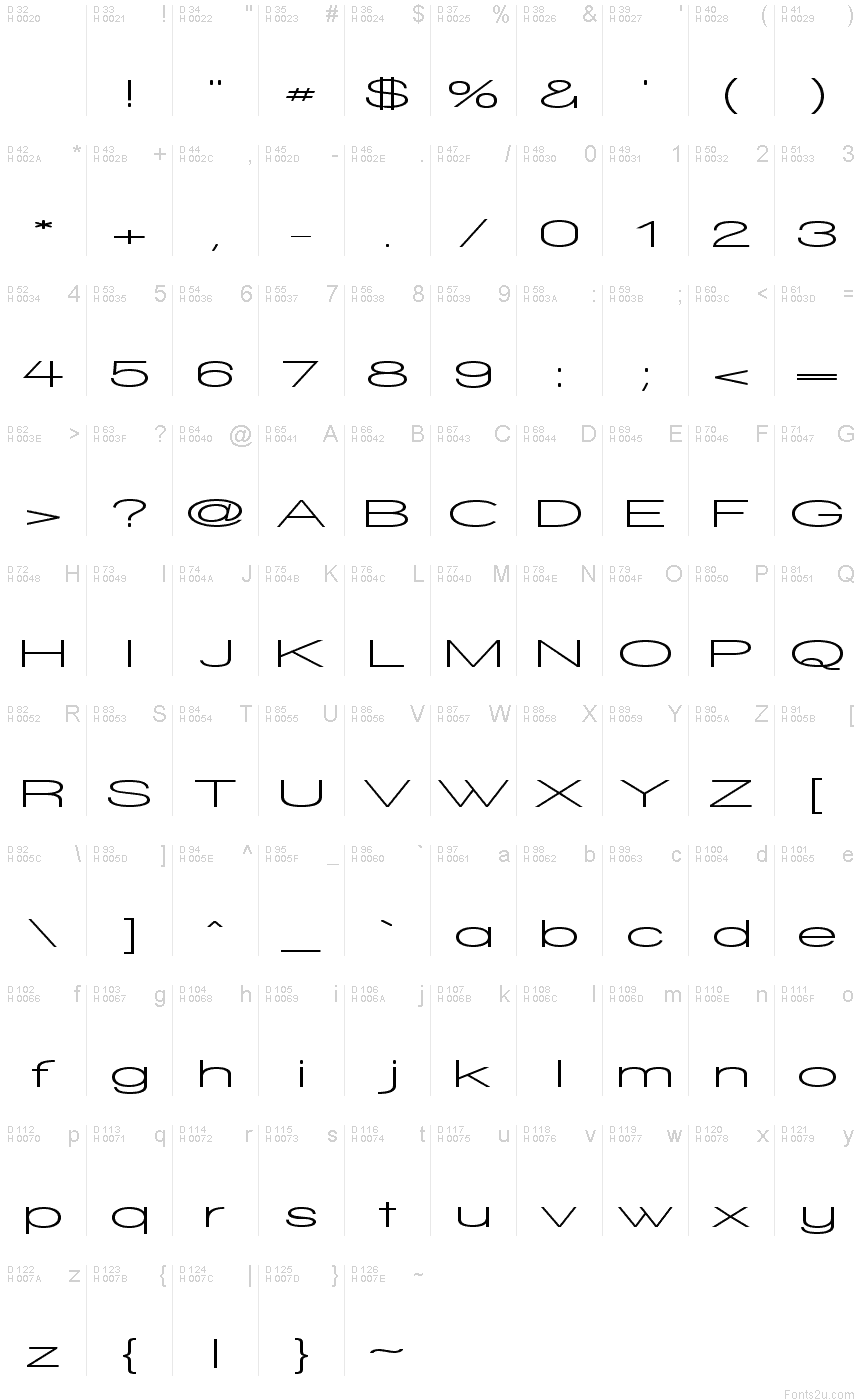
Walkway UltraExpand Bold
Walkway UltraExpand Bold di G.M. è un font sans serif geometrico gratuito con un'eleganza quasi futuristica. Le lettere appaiono ariose e architettoniche, costruite con tratti molto sottili, ampi spaziature e semplici forme circolari e angolari che mantengono il font nitido ed essenziale, evitando di risultare troppo carico.
Si adatta perfettamente a sistemi di branding, poster per gallerie, packaging tecnologico, copertine di riviste e titoli dove un font gratuito può conferire un mood cool ed essenziale senza ingombro visivo. Grazie alle forme minimali e allungate, funziona bene anche per titoli brevi, monogrammi e marchi testuali che necessitano di una silhouette pulita e spaziosa.